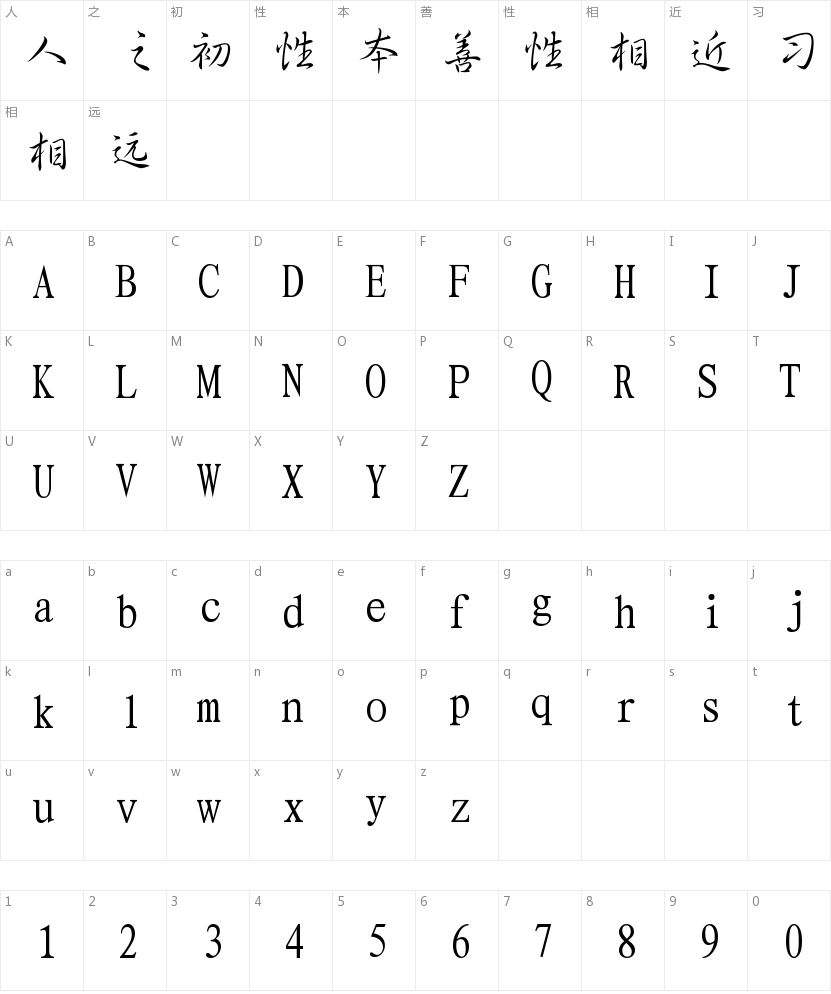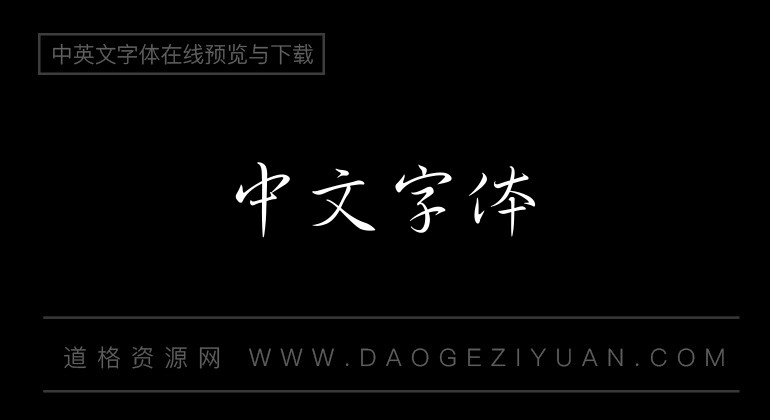
经典行书
经典行书是一种中国书法的传统字体,它以楷书为基础,但比楷书更加流畅,更加简洁,更加细腻,更加精致。经典行书的笔划细腻,虚实有致,笔画清晰,线条流畅,给人以恬静、典雅的感觉。在经典行书中,字的格式和笔画的连接更加自然,字的结构更加精致,给人以深沉、宁静的感受。
经典行书是一款非常不错的手写艺术字体,具有很好的视觉感,适合于文化类的宣传设计、商业类品牌的广告和产品包装设计以及个性化文字排版等较多场景。